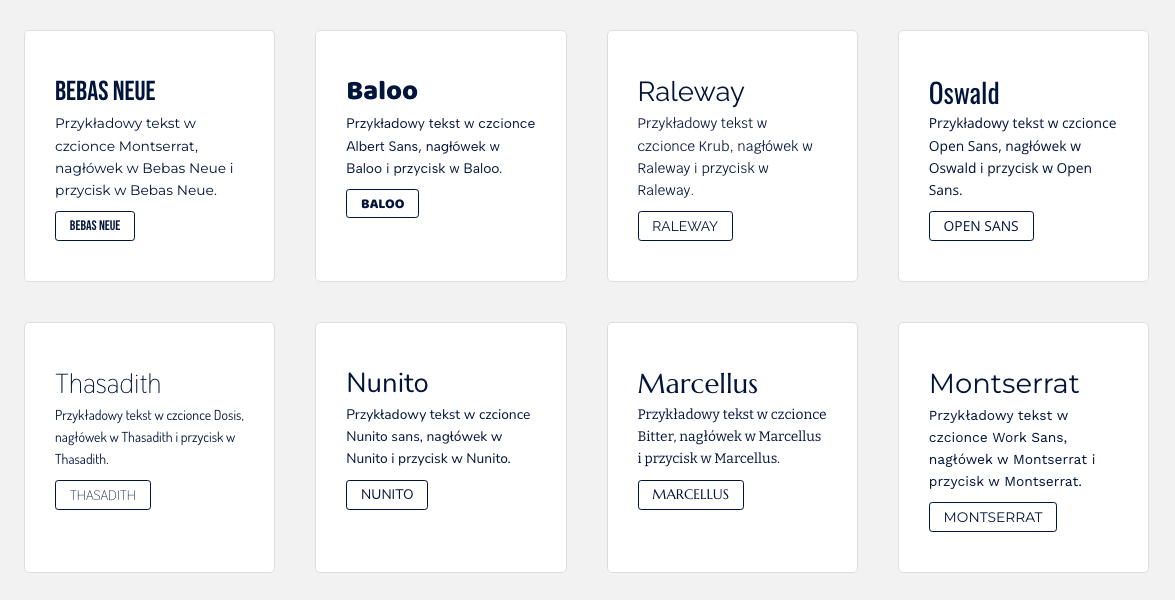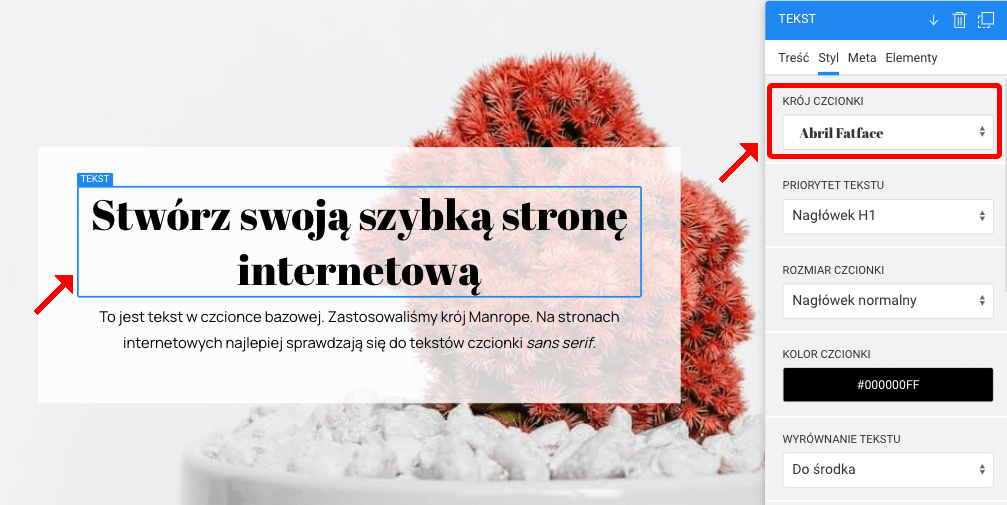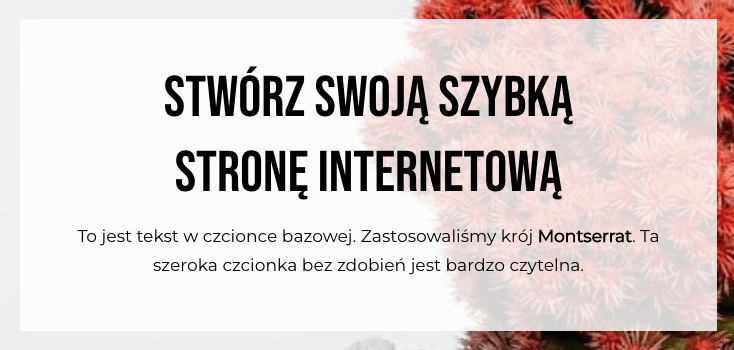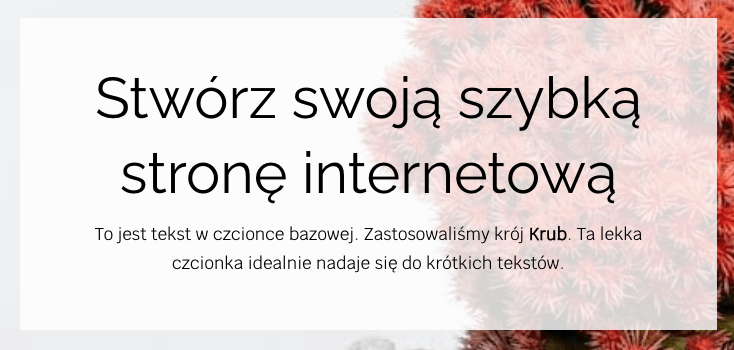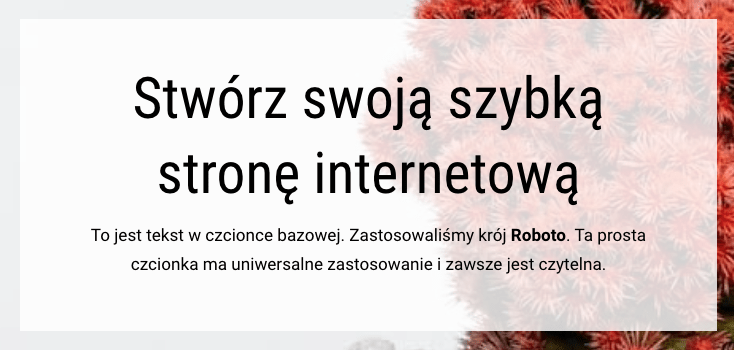
Wybór czcionki na stronie internetowej zależy od wielu czynników, takich jak tematyka strony, charakter marki czy styl projektu. Oto kilka wytycznych:
Polecamy zastosować maksymalnie 3 rodzaje czcionek na stronie. Dzięki temu strona będzie przejrzysta, czytelna i szybko się załaduje na każdym ekranie.
Font czy czcionka? Font to zestaw czcionek o określonych cechach zapisany w postaci elektronicznej. Na stronach internetowych wybieramy więc fonty. W potocznym języku nadal jednak font nazywany jest po prostu czcionką. W polskich wersjach popularnych aplikacji biurowych font także jest czcionką. Użytkownicy nadal częściej szukają w internecie czcionek niż fontów. Dlatego w tym wpisie będziemy używać częściej słowa czcionka.
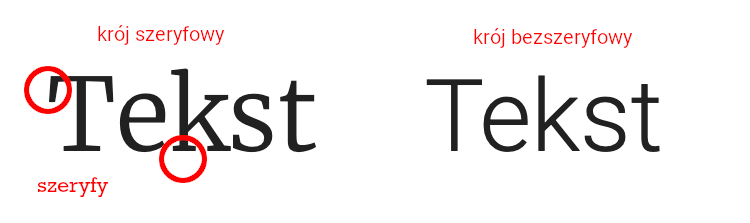
Kroje szeryfowe (serif) charakteryzują się zakończeniami - niewielkimi dekoracyjnymi elementami - na końcach liter. Czcionki szeryfowe są często uważane za bardziej czytelne w dłuższych blokach tekstu, takich jak artykuły lub książki drukowane. Te małe zakończenia liter pomagają oku szybciej śledzić linię tekstu. Kroje szeryfowe często kojarzą się z bardziej klasycznym i formalnym wyglądem. Potwierdzono w badaniach, że wzbudzają zaufanie dlatego często stosowane są na stronach z branż prawniczych, finansowych, ubezpieczeniowych.
Czcionki szeryfowe zazwyczaj używa się w książkach, e-bookach, gazetach i innych materiałach przeznaczonych do dłuższego czytania. Mogą być również stosowane na stronach internetowych, szczególnie jeśli witryna ma tradycyjny charakter.
W czytnikach e-booków typu Kindle, ReadEra masz do wyboru głównie czcionki szeryfowe, które są idealne do długiego czytania książek np. czcionka Bookerly, Droid Serif, Merriweather, Noto Serif mają kroje szeryfowe.
Skojarzenia związane z czcionką szeryfową: tradycja, elegancja, solidność, powaga, klasyka, respekt, zaufanie, lojalność.
Przykłady czcionek szeryfowych:
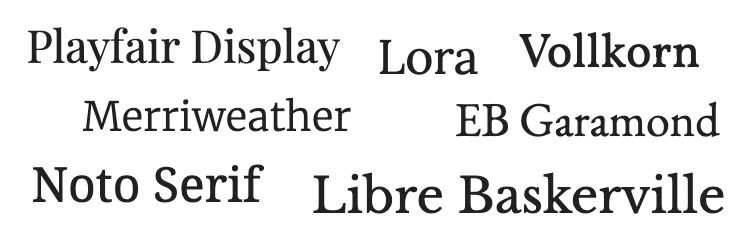
Krój Slab Serif to odmiana czcionki Serif, w której zakończenia liter mają wyraźne i masywne belki poziome (tzw. "slaby serif"). Te dodatkowe belki nadają literom bardziej masywny i solidny wygląd w porównaniu do tradycyjnych krojów szeryfowych, co może być użyteczne w nagłówkach o wyrazistym charakterze. Krój Slab Serif jest często wykorzystywany tam, gdzie projektanci chcą połączyć elementy tradycji z nowoczesnością, nadając tekstowi mocny wygląd. W dłuższych blokach tekstowych jest bardzo rzadko stosowany.
Skojarzenia związane z czcionką szeryfową slab: siła, męskość, wyrazistość, stabilność, pewność siebie.
Przykłady czcionek szeryfowych slab:
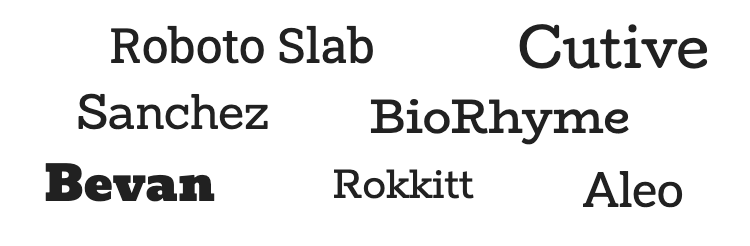
Kroje czcionek bezszeryfowych (sans-serif) są pozbawione zakończeń liter, co nadaje im bardziej czysty i prosty wygląd. Ze względu na swoją prostotę i czystość, kroje sans-serif są często preferowane w projektach online: w nagłówkach, tytułach, opisach, przyciskach, krótkich blokach tekstu. Te kroje są często kojarzone z nowoczesnym i minimalistycznym stylem. Kroje bezszeryfowe najczęściej stosowane są w sklepach internetowych.
Skojarzenia związane z czcionką bezszeryfową: nowoczesność, czystość, prostota, stabilność, obiektywizm, młodość.
Przykłady czcionek bezszeryfowych:
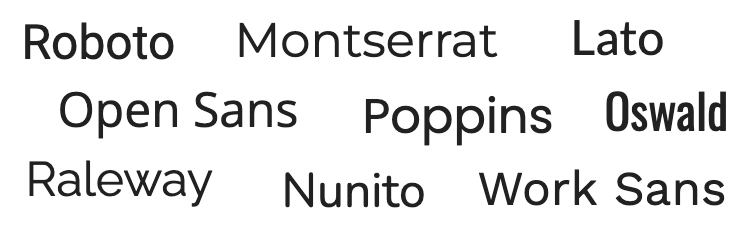
Czcionki stylizowane na pismo odręczne, przypominające kaligrafię to osobna kategoria. Te czcionki są starannie zaprojektowane, aby naśladować efekt pisania ręcznego, często z uwzględnieniem nieregularnych kształtów liter i różnic w grubości linii, co nadaje im unikalny, artystyczny charakter. Krój script nadaje się dla marki, nagłówka lub krótkiego akcentu tekstowego np. na zaproszeniu. Nie poleca się pisma odręcznego do dłuższych tekstów gdyż jest zbyt dekoracyjne a przez to nieczytelne.
Skojarzenia związane z czcionką szeryfową slab: indywidualność, kreatywność, elegancja, przyjazność.
Przykłady czcionek pisma odręcznego script:
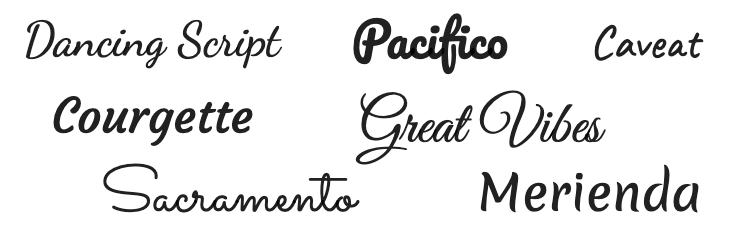
Ostateczny wybór czcionki zależy od kontekstu projektu i jego charakteru, a także od gustu projektanta. W praktyce wiele projektów łączy dwa rodzaje krojów czcionek: szeryfowy i bezszeryfowy, używając jeden krój dla treści głównego tekstu a drugi dla elementów nagłówkowych i akcentów. Przykładowo w Wikipedii używana jest czcionka szeryfowa dla tytułu hasła, natomiast dla definicji i opisów stosowana jest czcionka bezszeryfowa. Drugą praktyką jest zastosowanie jednego kroju czcionki dla całej witryny a tylko pogrubienie czcionki w nagłówkach.
Na stronie Najszybszej używamy czcionki o kroju bezszeryfowym Manrope dla nagłówków i tekstów oraz czcionki Archivo dla przycisków. W kreatorze możesz korzystać z szerokiego wyboru ładnych, nowoczesnych czcionek dostępnych w kolekcji Google Fonts. Najpopularniejszymi wyborami są m.in. Roboto, Open Sans, Lato, Poppins, Montserrat, Inter, Noto, Nunito, Source Sans Pro, Works Sans i najnowsza czcionka Google Sans Flex. Przed dokonaniem wyboru, możesz zobaczyć ich podgląd w Kreatorze (niżej w artykule znajdziesz ich wizualizacje).